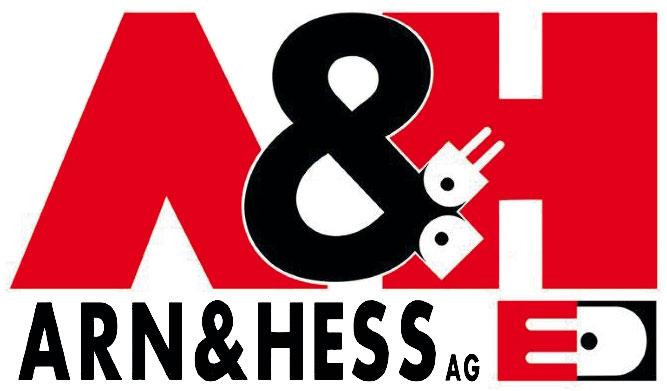
Logo-Schriftart (Arn & Hess)
Für unseren Kunden Arn & Hess müssen wir das Logo neu erstellen, da die Originaldatei nicht mehr vorhanden ist. Das Logo wird zum Druck sowie für die Webseite verwendet. http://www.arnhess.ch
Arg verbasteltes Logo, der Zusatz ARN & HESS ist hier und auf der Website zudem unterschiedlich, Basis ist aber wahrscheinlich eine Futura (im obigen Beispiel elektronisch verschmälert, auf der Website ein condensed Schnitt). Am besten einen korrekten halbfetten condensed Schnitt verwenden.